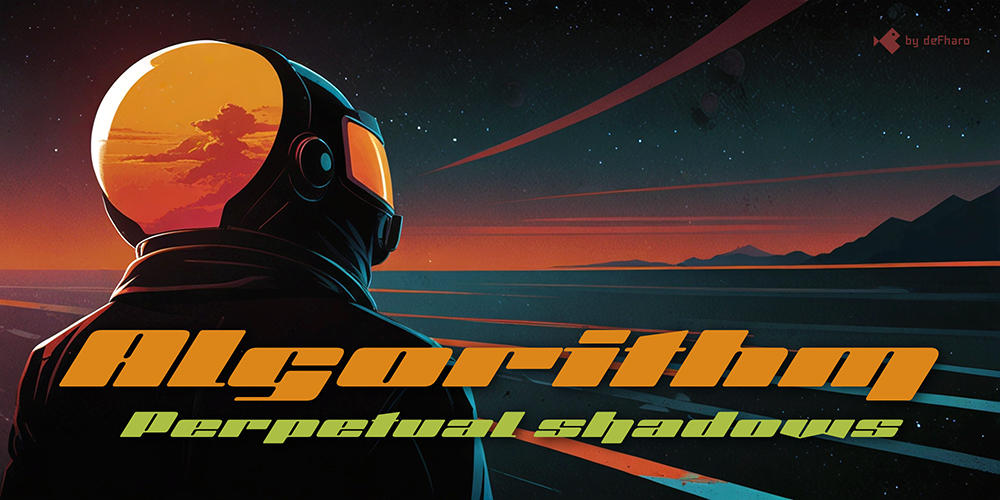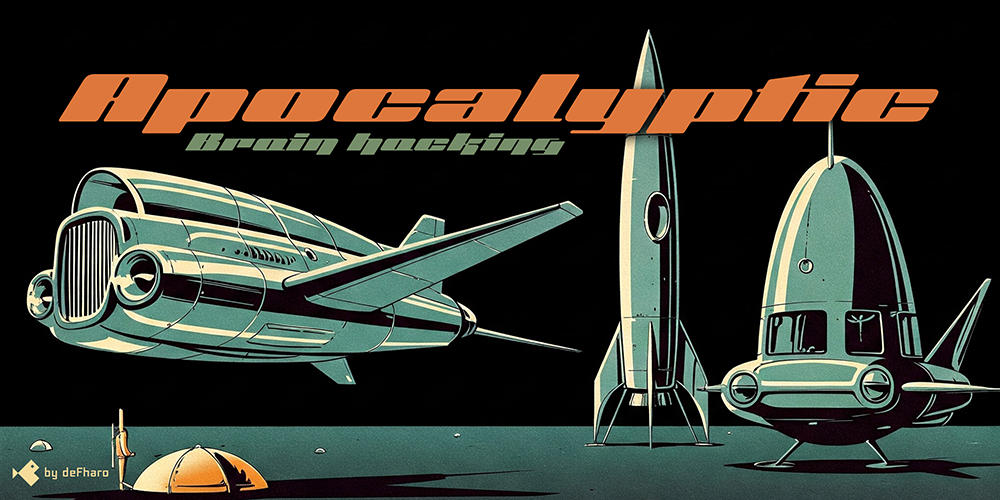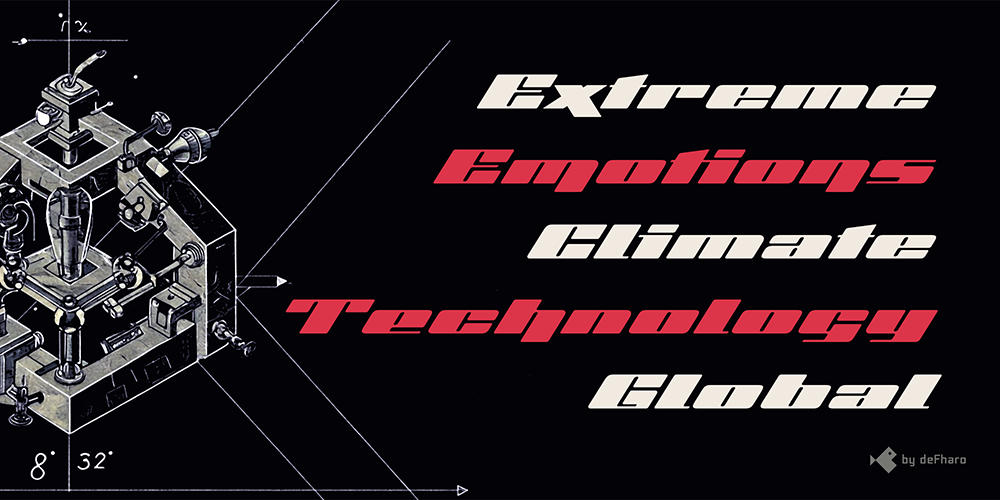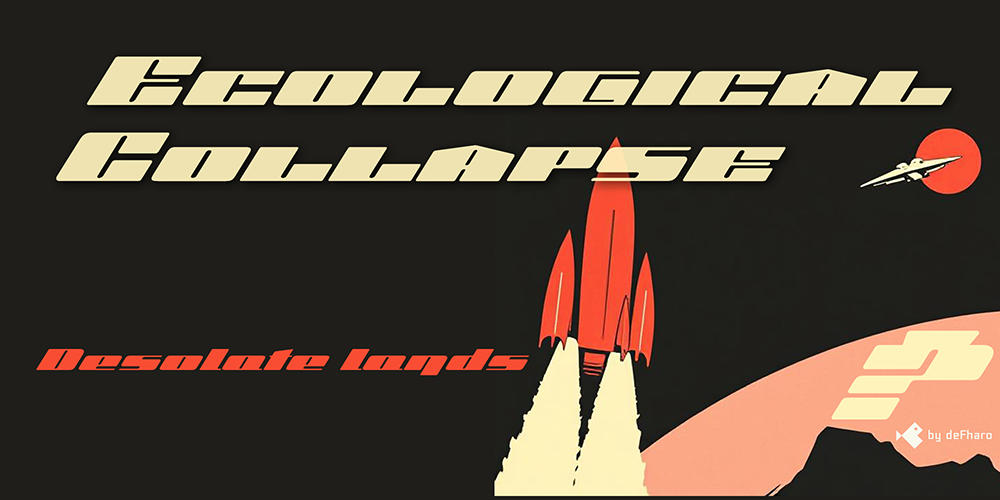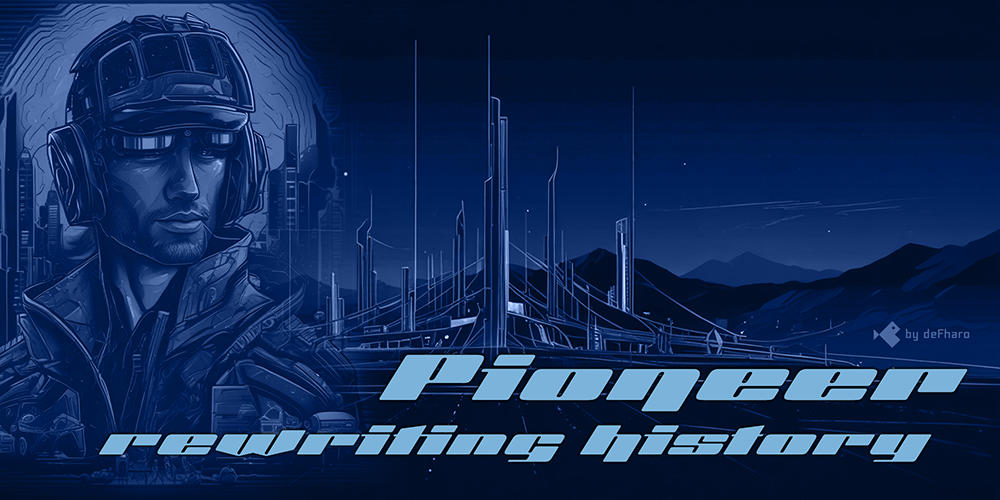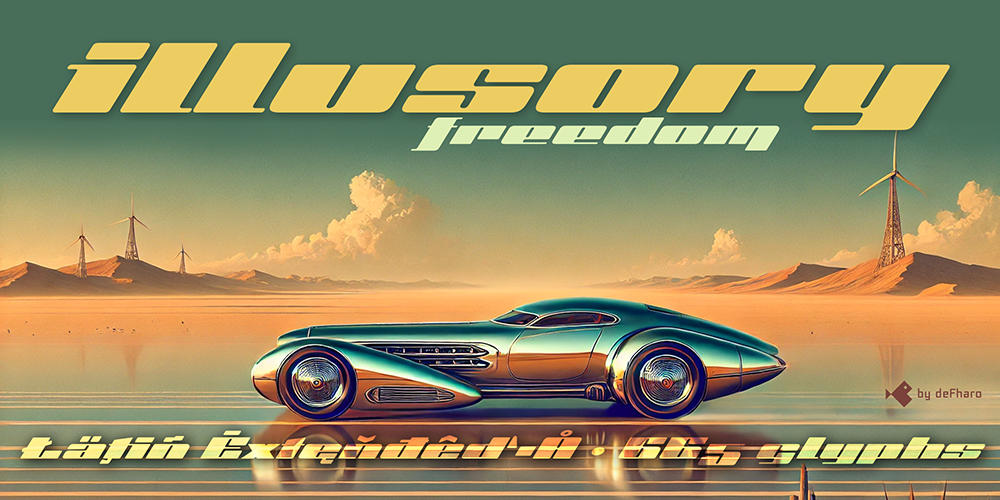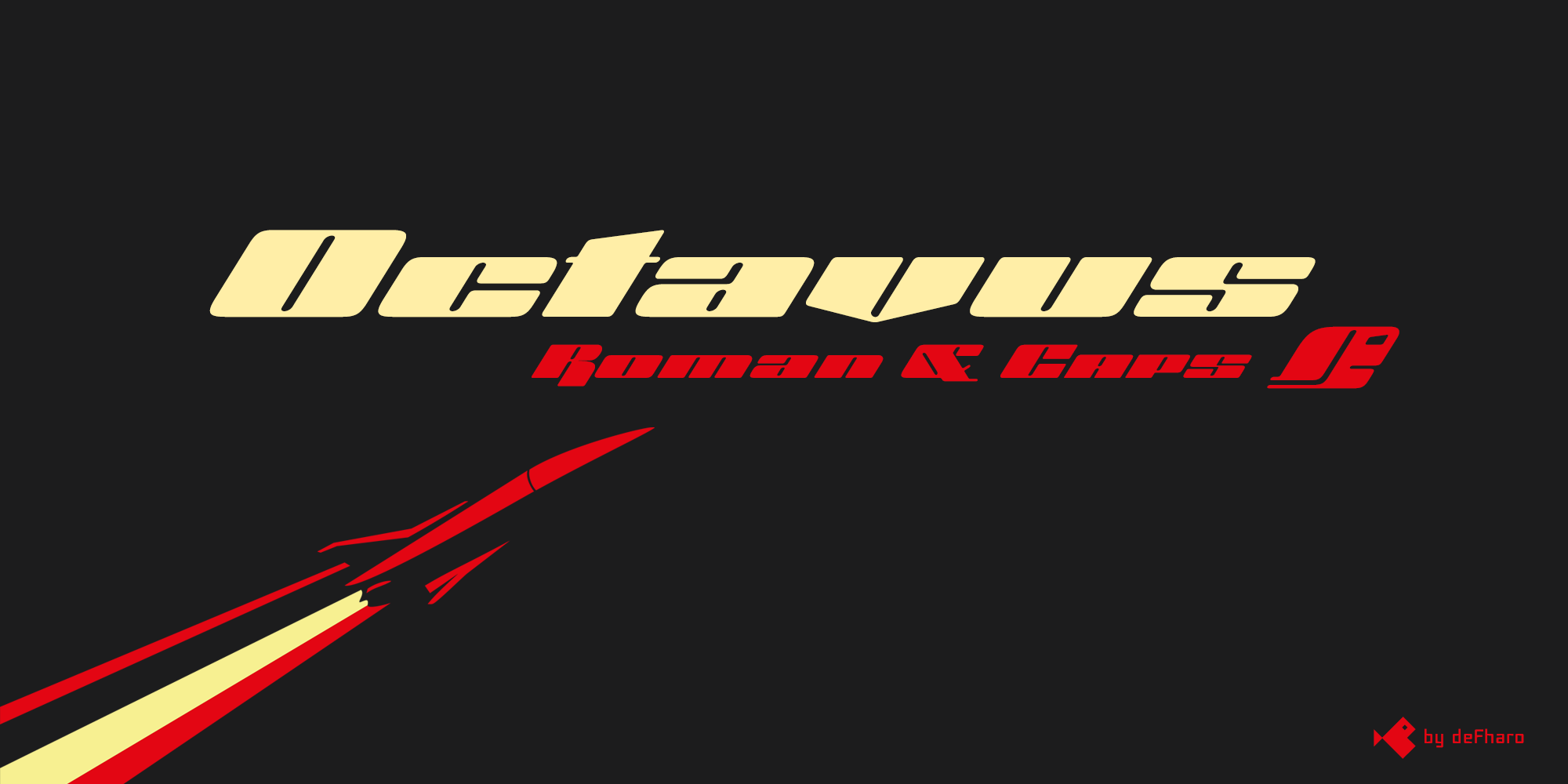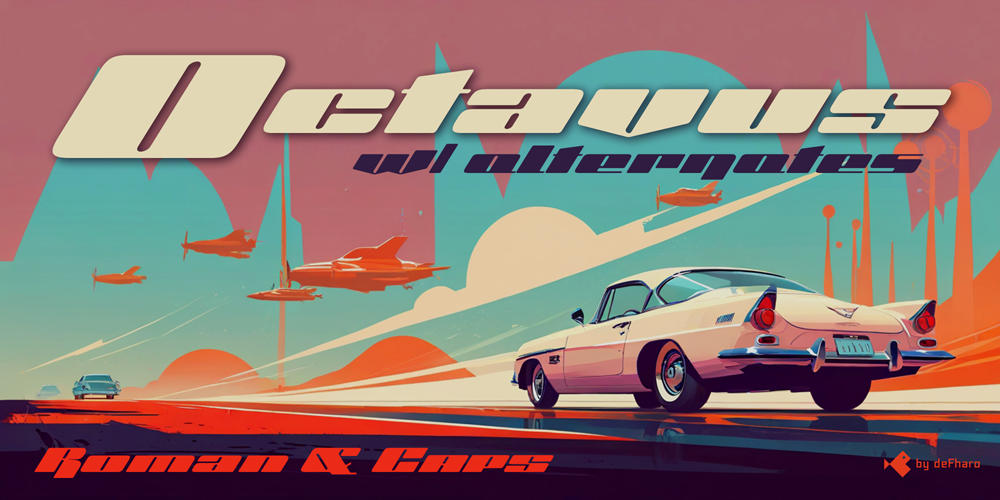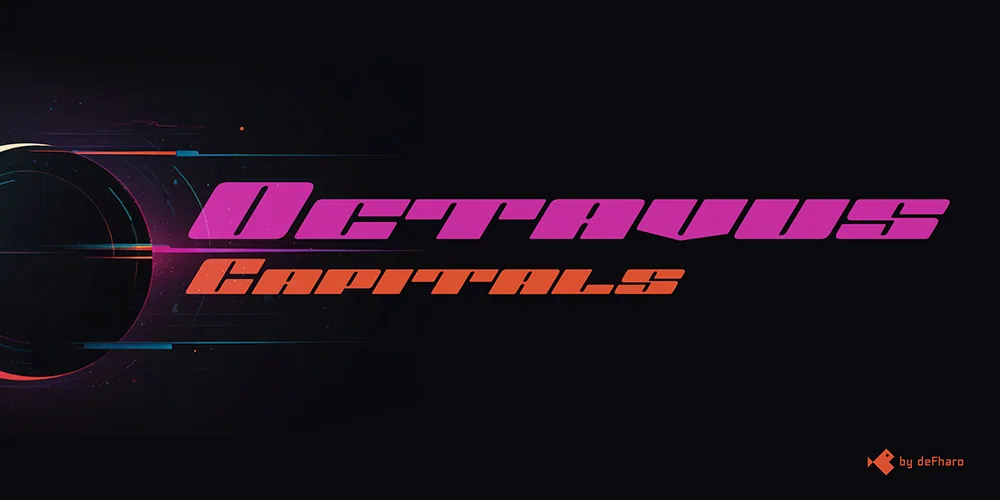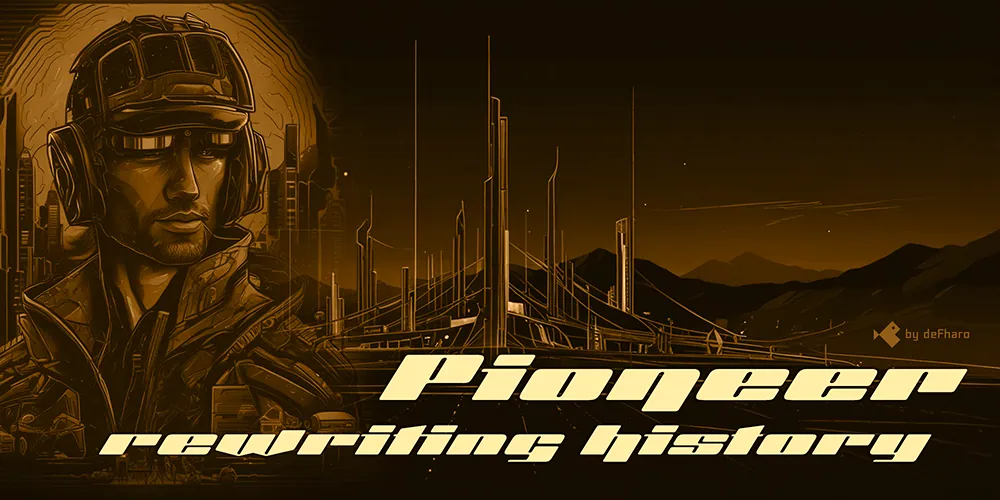
Se trata de una familia tipográfica robusta y atrevida, disponible en dos versiones: Roman y Capitals. Su proporción Expandida y su peso Black le otorgan una personalidad inconfundible.
Black & Extended
Estilo: Sans Serif, Slanted, Display, Chunky, Thickset, Roman
Proporción: Capitals, Small Caps, Inclined, Black
Alternates: 120
Octavus es una tipografía nacida de mi fascinación por el retro futurismo, la tecnología y el minimalismo audaz.
Quería crear algo que combinara la fuerza visual de lo clásico con la fluidez de lo moderno, y así surgió esta familia: rotunda, expandida y negra, con una inclinación de 32 grados que le da un dinamismo inconfundible, la he diseñado pensando en el impacto y la presencia.
Se trata de una familia tipográfica robusta y atrevida, disponible en dos versiones: Roman y Capitals. Su proporción Expandida y su peso Black le otorgan una personalidad inconfundible.
La inclinación de 32 grados le confiere una sensación dinámica única, su estética fusiona la actualidad, el Futuro y la tecnología, y sin duda, les transportará a universos futuros. Es gruesa, rotunda, moderna, con un contraste dramático entre sus astas horizontales y verticales. Cada letra, con un acabado redondeado y gran inclinación, crea un contexto visual increíblemente dinámico y tecnológico con connotaciones vintage.
Además quería que fuera funcionalmente potente, por eso integré funciones OpenType avanzadas —letras alternativas, fracciones dinámicas, símbolos matemáticos, etc.— para que los diseñadores pudieran explotar su versatilidad.
Cada curva, cada terminal redondeado, y hasta el más mínimo ajuste de kerning fueron pensados para que, incluso en su máxima expresividad, nunca sacrificara la legibilidad en tamaños grandes.
Para su presentación visual, he seleccionado ambientes distópicos, retro futuristas o directamente tecnológicos, siempre manteniendo un enfoque minimalista y jugando con altos contrastes de color. El objetivo es que Octavus no sólo cumpla su función tipográfica, sino que también ayude a evocar atmósferas únicas cargadas de significados.
Pero Octavus no es solo nostalgia; es un puente entre ese futuro imaginado y el diseño actual. Por eso brilla en diversos usos y medios —donde cada palabra debe imponerse con personalidad.
- Títulos y encabezados impactantes
- Folletos y posters
- Señalética y cartelería exterior
- Logotipos y branding
- Embalaje de productos
Con Octavus, tus mensajes no pasarán inadvertidos: cada letra hablará por sí misma, proyectando fuerza, dinamismo y un sello inconfundible de sofisticación tecnológica. Espero que disfrutes utilizándola tanto como yo he disfrutado creándola.